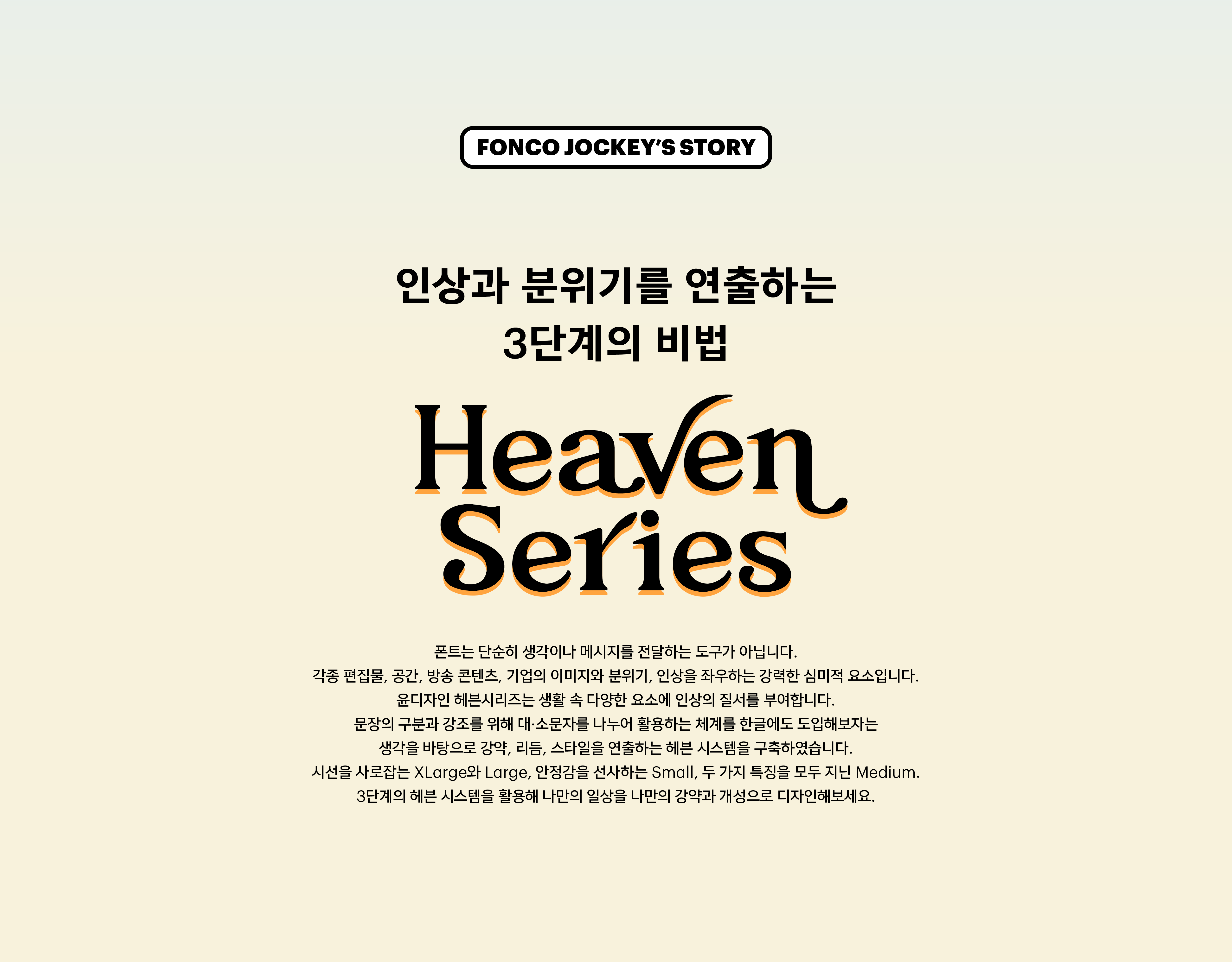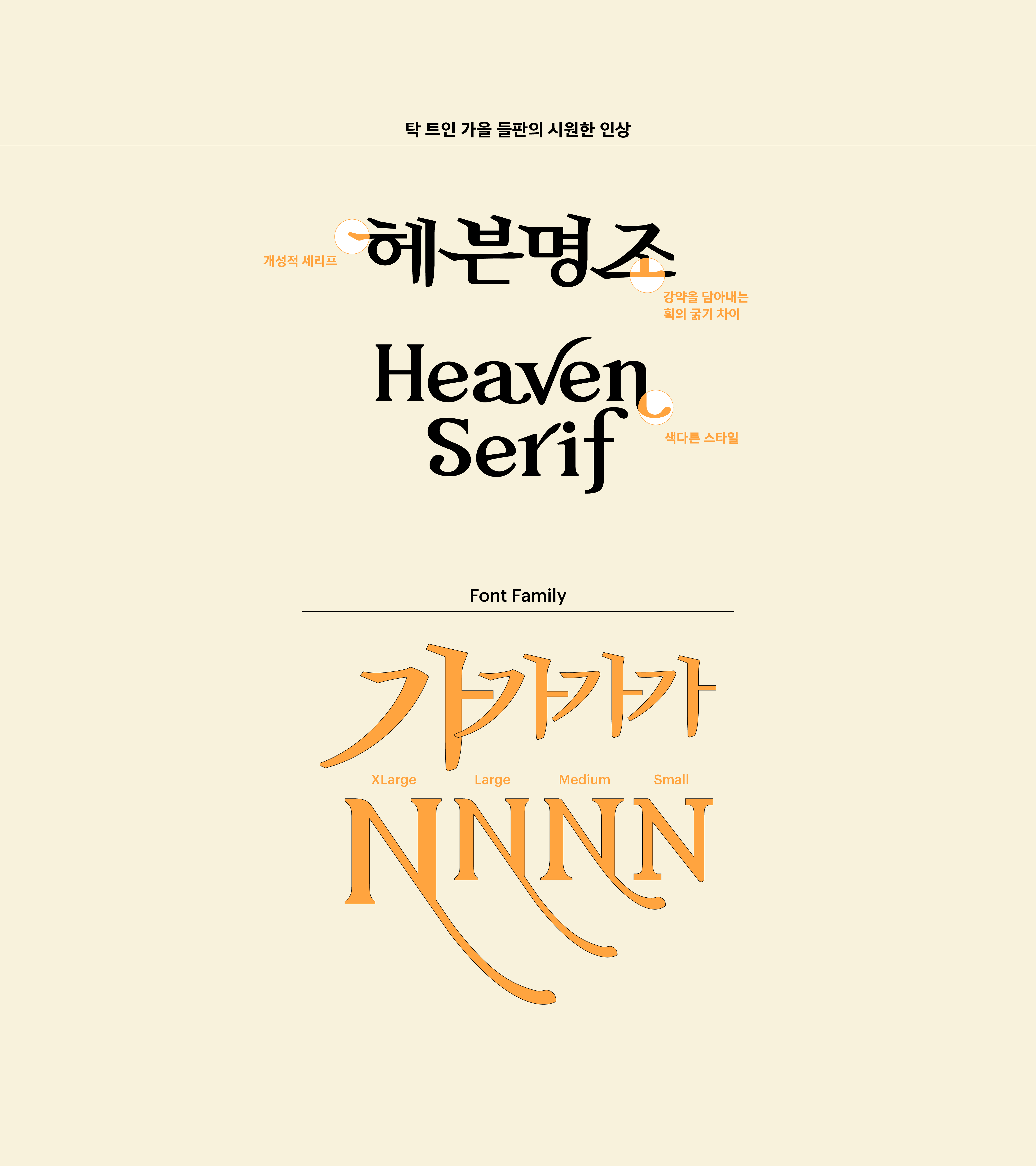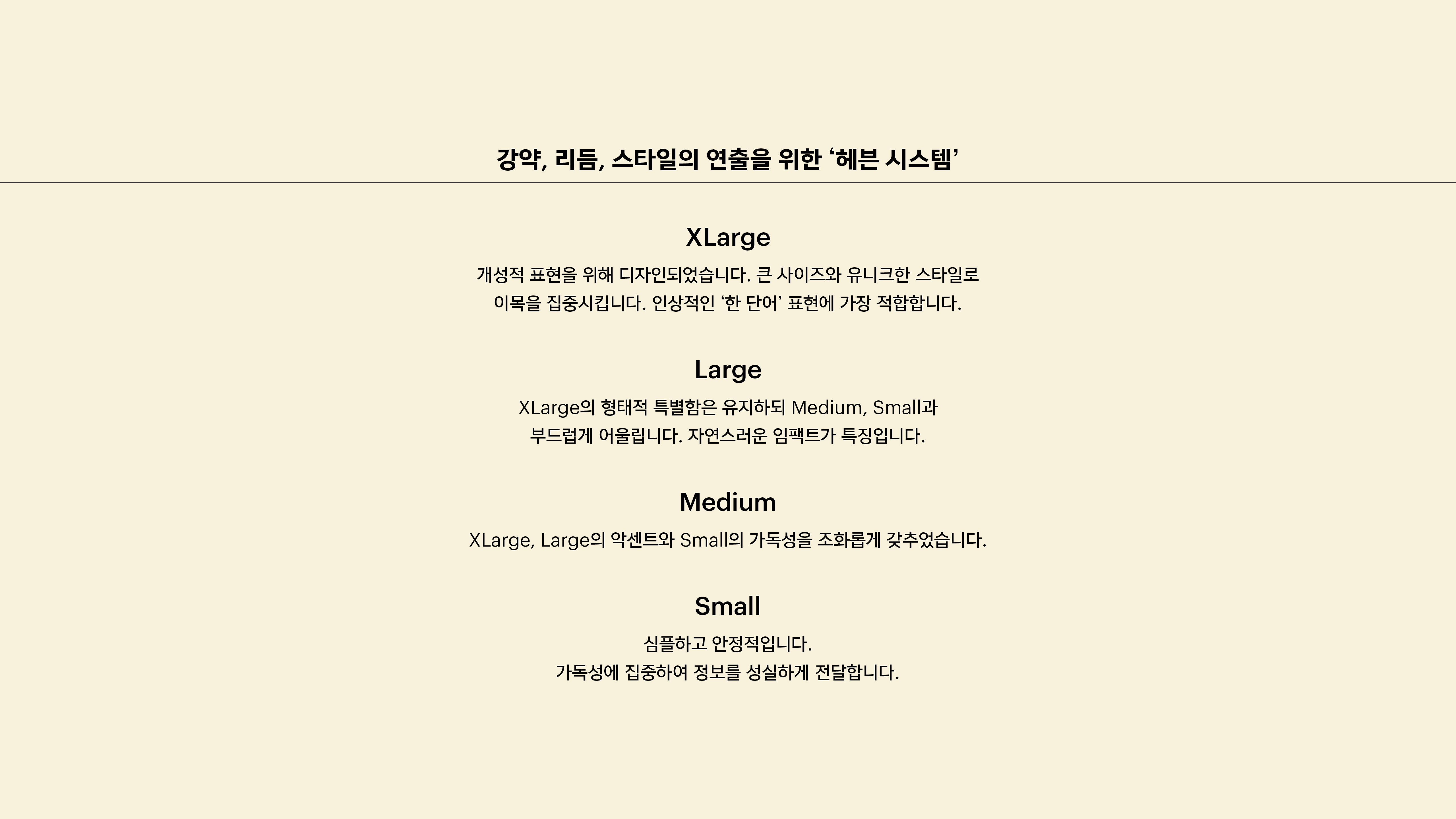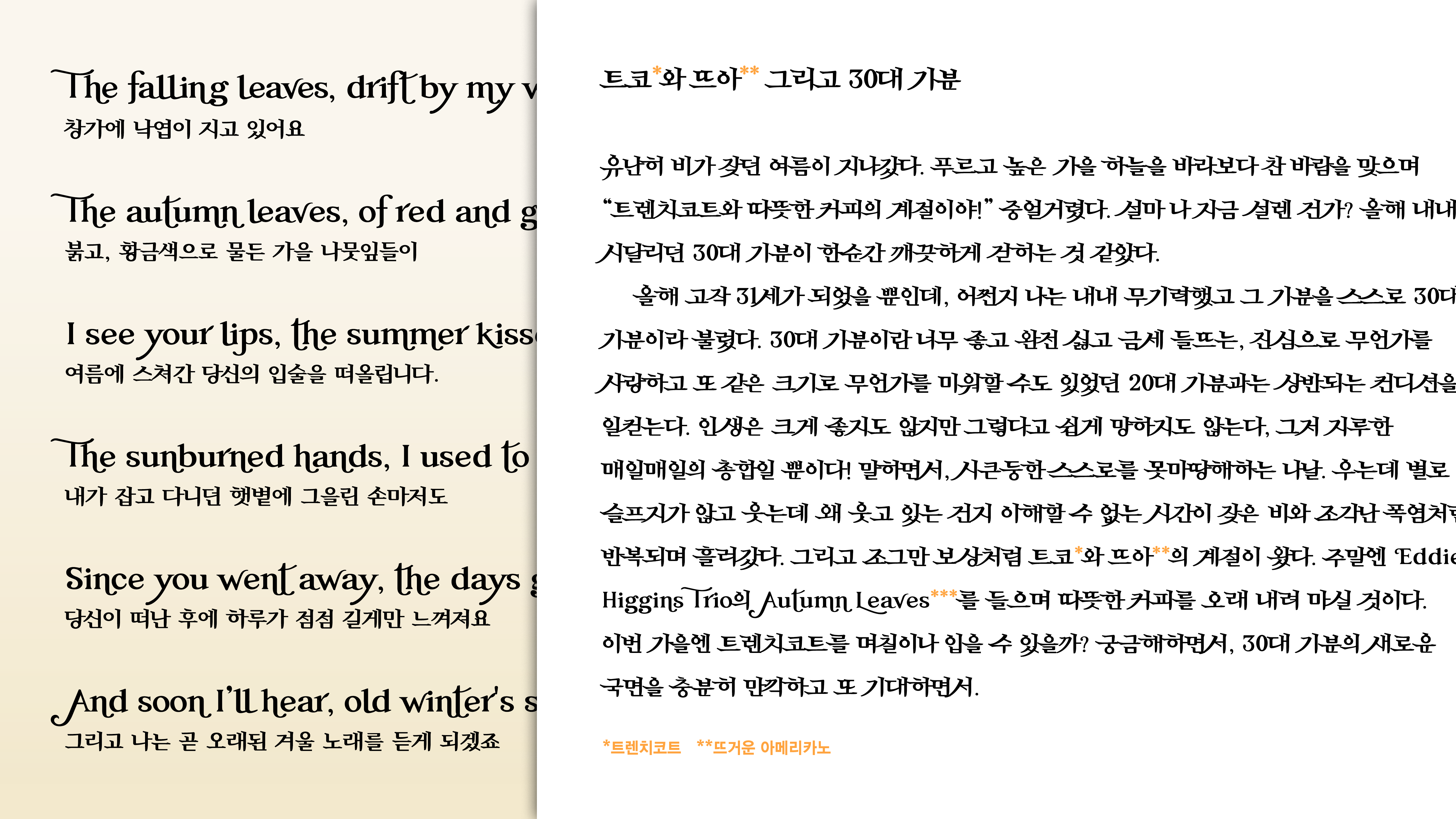
폰트는 단순히 생각이나 메시지를 전달하는 도구가 아닙니다. 각종 편집물, 공간, 방송 콘텐츠, 기업의 이미지와 분위기, 인상을 좌우하는 강력한 심미적 요소입니다. 윤디자인 헤븐시리즈는 생활 속 다양한 요소에 인상의 질서를 부여합니다. 문장의 구분과 강조를 위해 대소문자를 나누어 활용하는 체계를 한글에도 도입해보자는 생각을 바탕으로 강약, 리듬, 스타일을 연출하는 헤븐 시스템을 구축하였습니다. 시선을 사로잡는 XLarge와 Large, 안정감을 선사하는 Small, 두 가지 특징을 모두 지닌 Medium. 3단계의 헤븐 시스템을 활용해 나만의 일상을 나만의 강약과 개성으로 디자인해보세요.
Yoon 헤븐명조